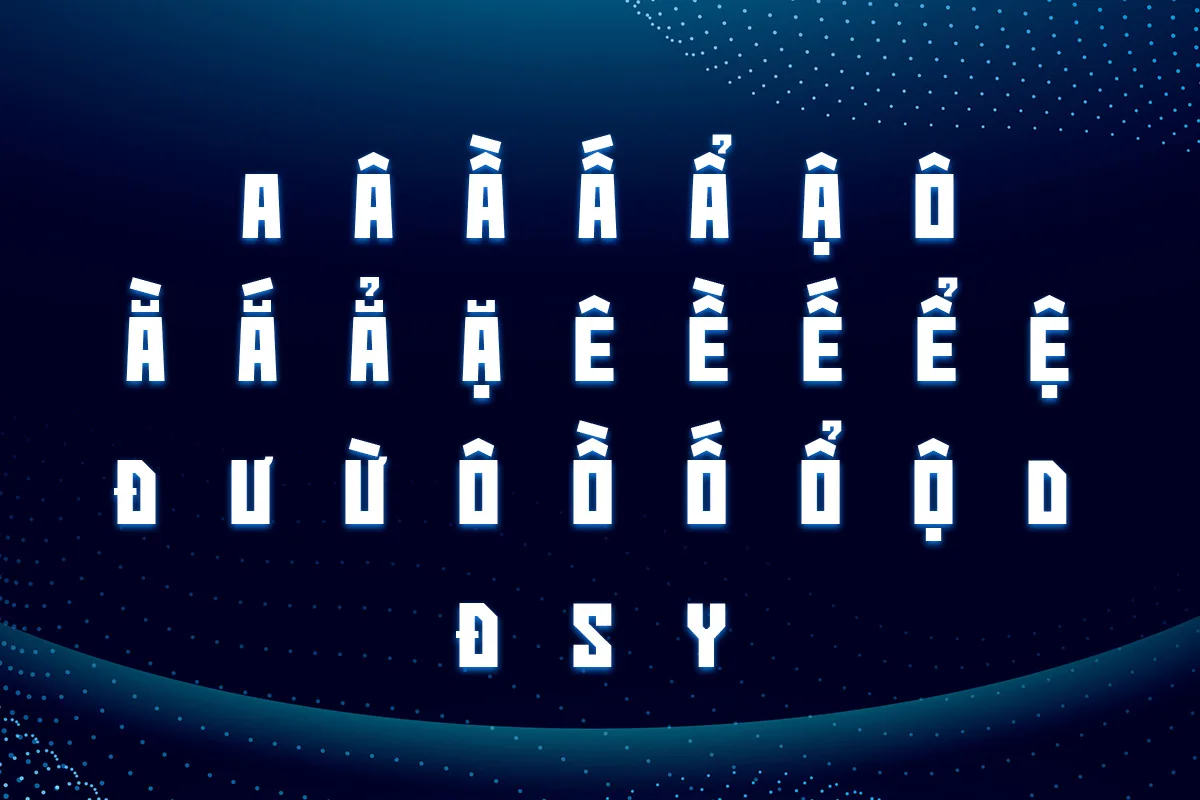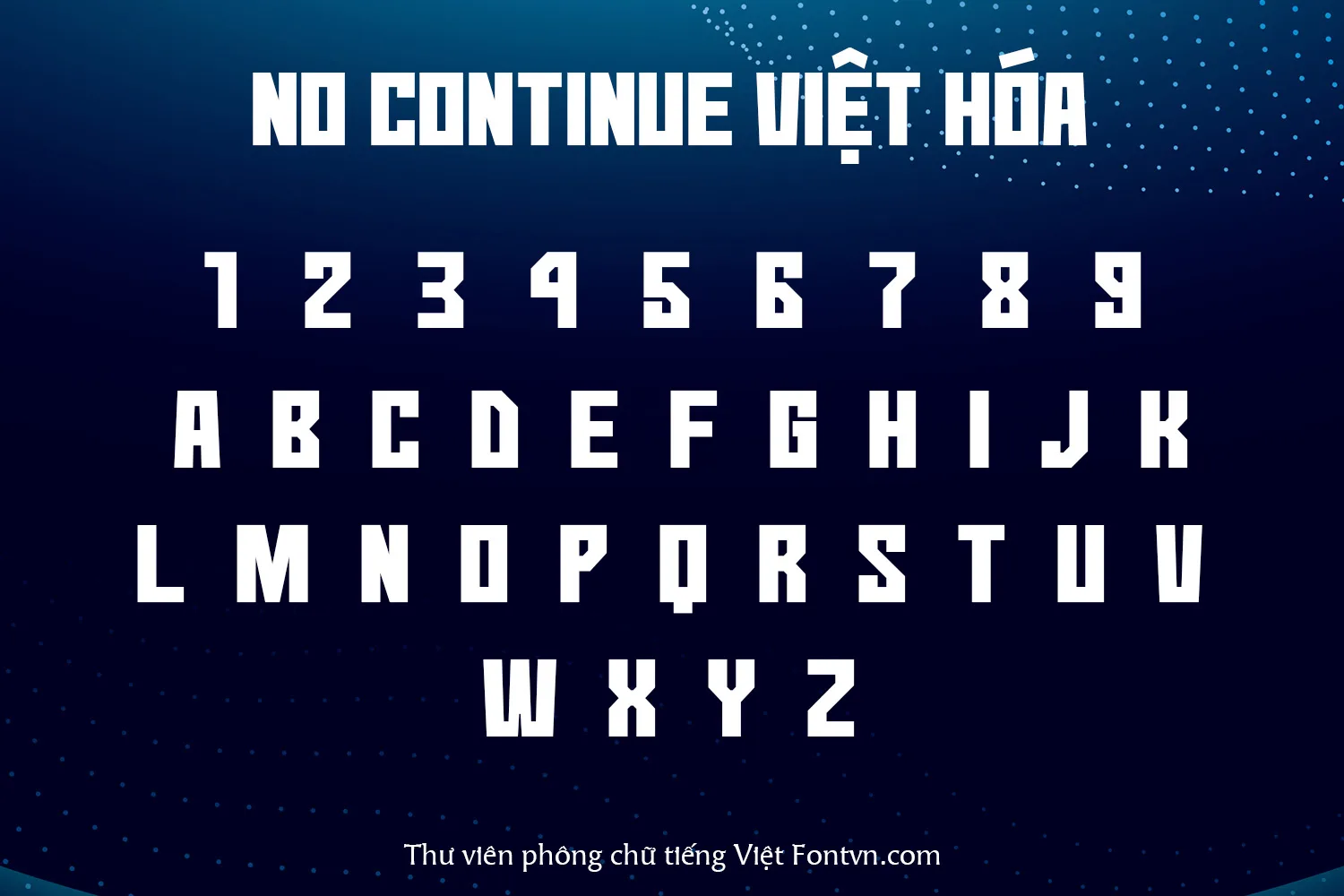
DVN – No Continue Việt hóa – Kiểu chữ cắt khối mạnh mẽ cho thiết kế đậm chất công nghệ
Font No Continue là một kiểu chữ đậm chất retro, được Việt hóa. Thiết kế của font mang phong cách mạnh mẽ, cứng cáp, với các đường nét vuông vức, tạo cảm giác như được cắt ghép từ các khối hình học. Đặc trưng của No Continue nằm ở những chi tiết bị “cắt ngang” hoặc thiếu hụt một phần nét, mang đến vẻ phá cách và đầy tính công nghệ, rất phù hợp cho các thiết kế game, tiêu đề poster, hoặc nội dung mang màu sắc cyberpunk, arcade.
Bộ font hỗ trợ đầy đủ bảng chữ cái tiếng Việt, bao gồm chữ hoa, chữ thường và số. Tuy không có nhiều nét cong mềm mại, No Continue lại thu hút bởi cá tính riêng biệt và khả năng tạo điểm nhấn thị giác mạnh. Nếu bạn đang tìm một font Việt hóa độc đáo, ấn tượng để gây chú ý trong các thiết kế đậm chất hoài cổ hoặc kỹ thuật số, đây là lựa chọn không nên bỏ qua.